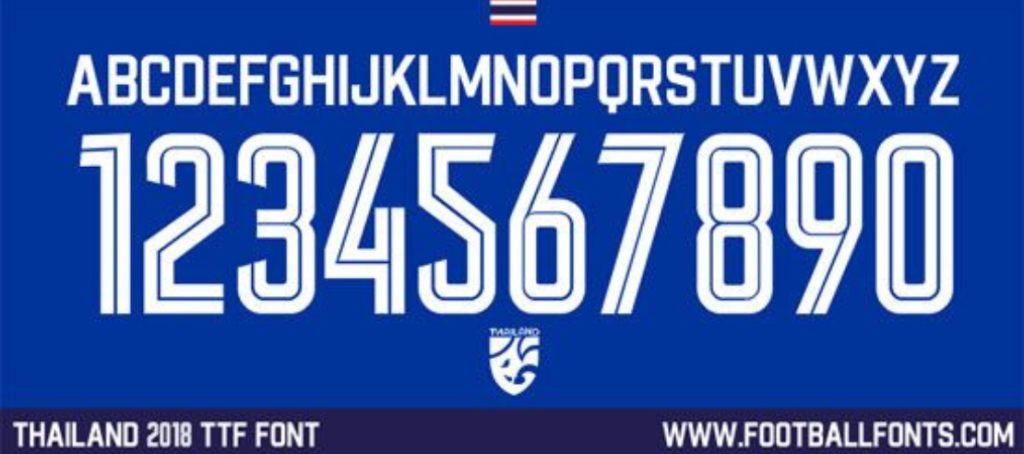
Bộ Font: Font football
Phân loại: Mạnh mẽ, Thể thao
Font Football là một lựa chọn lý tưởng cho những ai đam mê thể thao, đặc biệt là bóng đá, và muốn tạo ra các thiết kế mang tính thể thao mạnh mẽ và năng động. Font Football là font chữ thuộc bộ font chữ không chân, với các đường nét dứt khoát, góc cạnh và đậm chất thể thao, Font Football giúp truyền tải tinh thần chiến đấu và sự kịch tính của môn thể thao vua. Dù bạn đang thiết kế áo đấu, poster cổ vũ, hay logo cho các giải đấu, Font Football sẽ giúp bạn tạo nên những sản phẩm đầy ấn tượng và thu hút người xem.